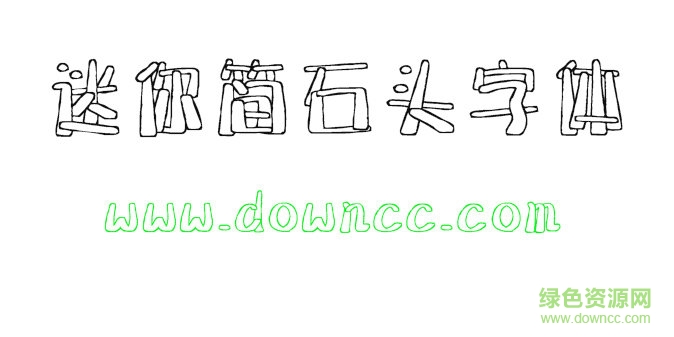
迷你简石头字体看起来就如一个个的石头堆叠在一起组成的字体,给你十分不错的视觉效果是用户在各类文件编辑中时尚选择到的有趣文字样式,为你代带来优秀的显示风格,需要的朋友就请来绿色资源网下载使用吧!
迷你简石头字体看起来有种凌乱的美,字体中空,像字体名字一样,也因其独特,常被用户用于各类设计行业,是款不错的字体。